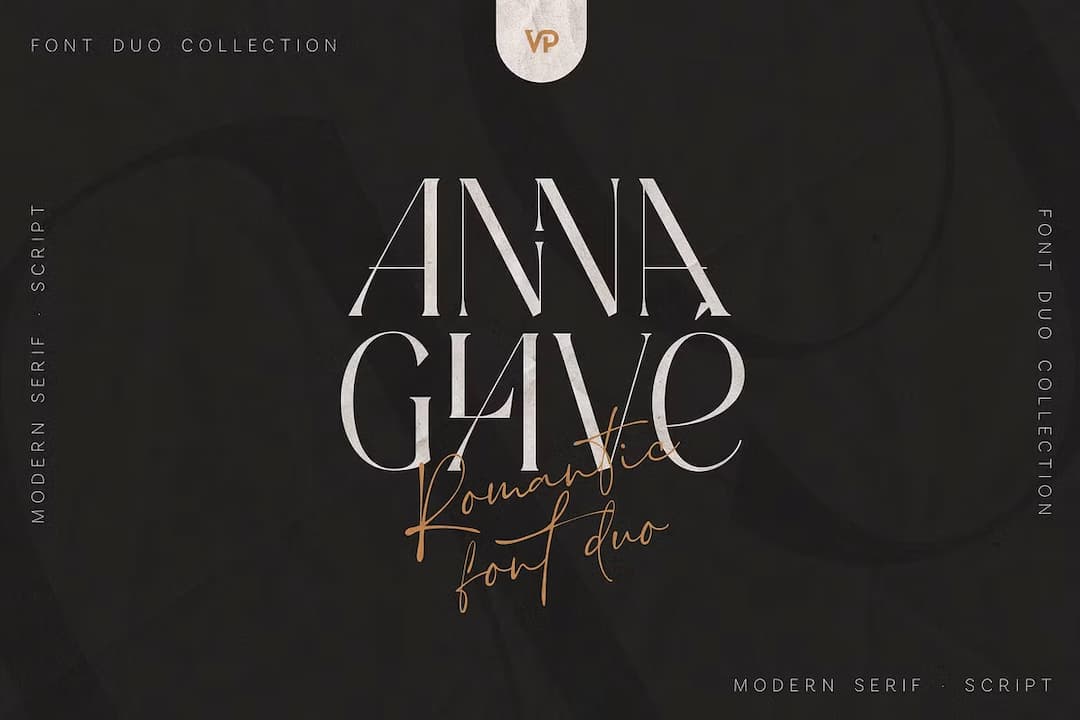
クラッシーなモダンローマンとスクリプトのデュオ。ローマンの方はややコンデンス気味でセリフはフレアっぽい。スクリプトはカリグラフィーというよりはシグネチャーと言った方がいいだろう。どちらも当然のようにリガチャーやオルタネートがあるが、ローマンのリガチャーは通常のストロークを共有するタイプと、画像の NN のようにストロークが短く分かれた変わったものもある。そこが他と違っていて個性的でおもしろい。